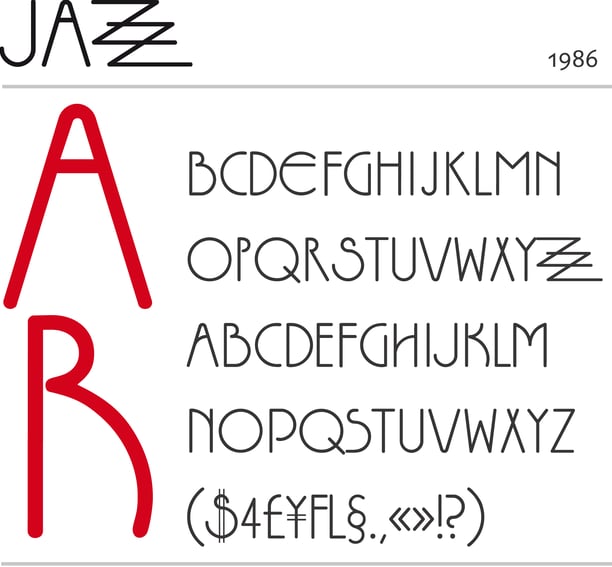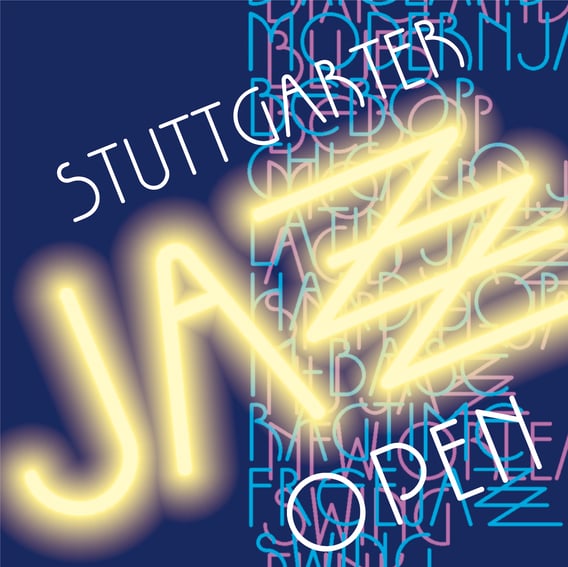
Jazz
Die Jazz ist eine reine Versalschrift, bei der die Groß- und Kleinbuchstaben zum Teil mit alternativen Formen belegt sind. Durch die gleichmäßige Linienstärke und die runden Abschlüsse wirkt sie wie mit der Pfannenfeder gezeichnet. Formal liegen die Wurzeln der »Jazz« in den 80er Jahren und im Jugendstil. Es gibt eine große Zahl ähnlicher Entwürfe (Busorama, Plaza, Premier Light-line usw.), so dass man die Jazz am ehesten als Fingerübung einstufen kann. Entwickelt habe ich sie 1986 für einen Buchrücken und für ein Plakat des Max-Born-Gymnasium-Jazz-Trio. Daher stammt auch das etwas eigenwillige doppelte z.